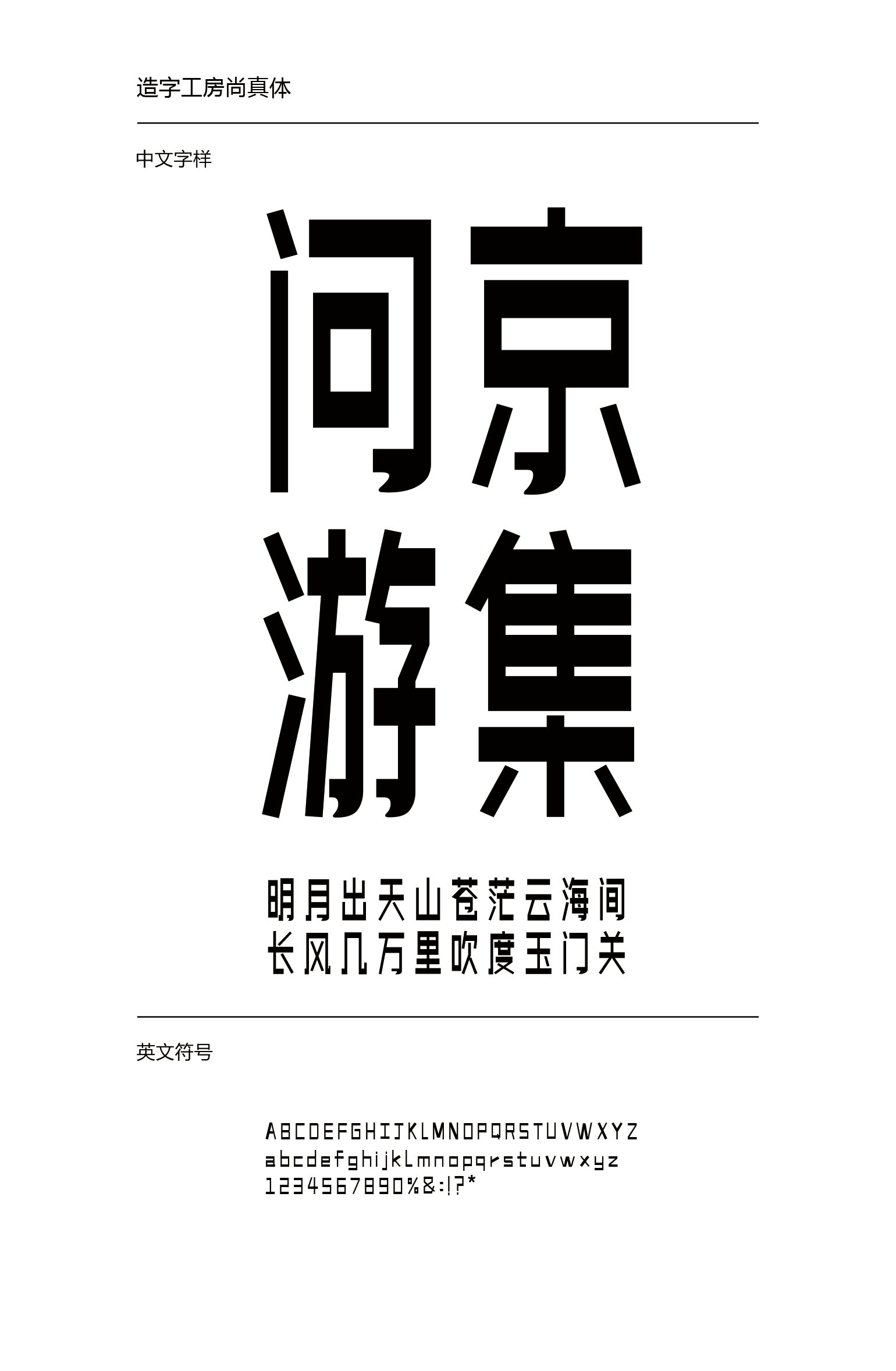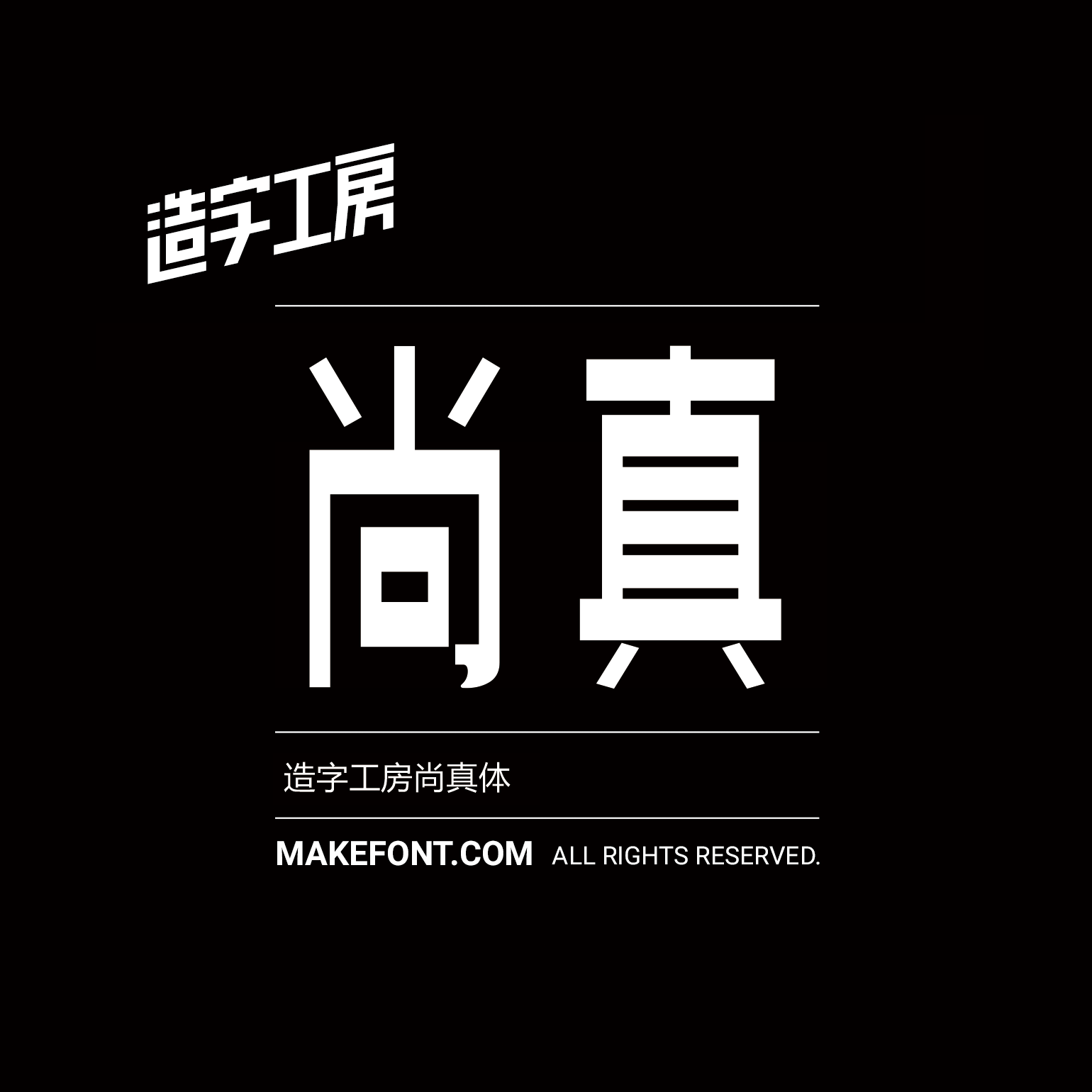
造字工房尚真体 造字工房尚真体设计说明 造字工房尚真体,其字瘦长、刚健质朴,结构严谨。钩画的处理令其在兼具黑体字严谨结构之外,不失灵动之感,特点鲜明。适用于大标题、品牌广告宣传等需要强力视觉表现的环境。本字体为简体字库,采用OpenType/CID格式,Adobe-GB1-5编码。基于中华人民共和国GB2312-80字符集标准,另按需添加101个汉字。共收容字数6864CJK汉字,ASCII常用字符100个。 造字工房尚真体下载地址 点击下载